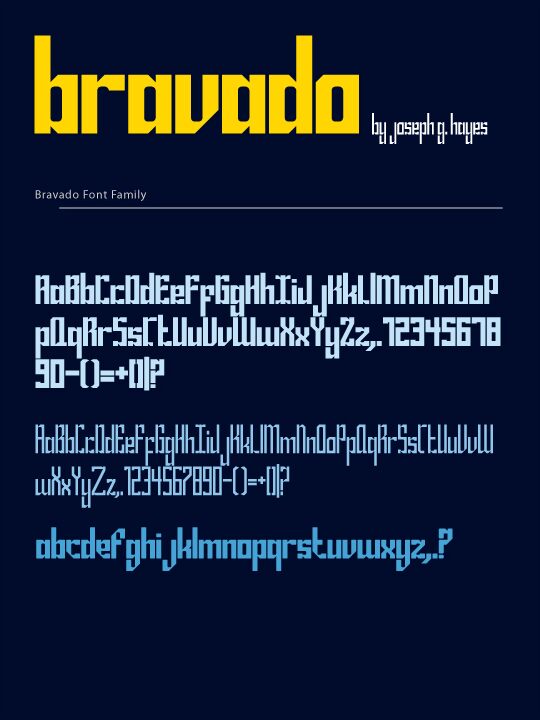
Bravado Block от Joseph Ghayes — это бесплатный техно-шрифт категории display с жестким модульным ритмом и современным минималистичным характером. Буквы выглядят как собранные из тяжелых прямоугольных блоков, с острыми врезками и квадратными просветами, которые придают начертанию импульс в стиле трафарета, не теряя при этом солидной монолитной формы.
Он отлично подходит для заголовков плакатов, названий игр, музыкального оформления, технологичного брендинга и титров, где короткие слова могут раскрыть эту компактную, выверенную текстуру. Будучи бесплатным шрифтом, он также хорошо работает в логотипах и монограммах, так как плотные формы и повторяющиеся детали делают даже несколько букв визуально цельными и графичными.